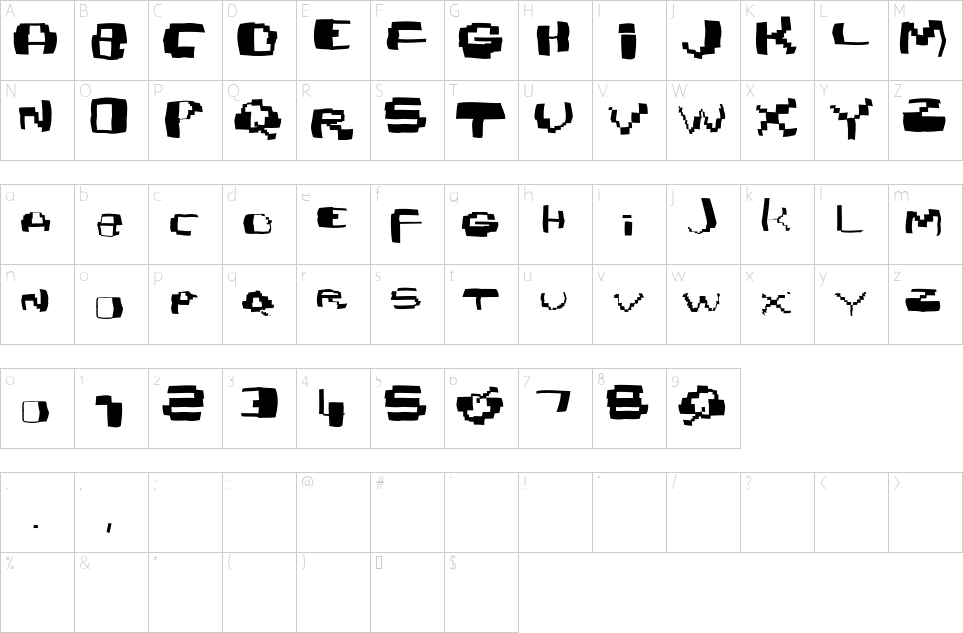
A Damaged Pix Font é uma fonte única e intrigante que traz uma personalidade única para seus projetos. Desenhada pelo designer desconhecido Manfred Klein 击破, ela combina elementos de desgaste, danos e imperfeição de uma maneira que torna qualquer texto a qual ela é aplicado um verdadeiro show de palco. Se você está procurando por algo além do convencional, essa fonte pode ser perfeita para dar aquele toque especial em seus designs digitais. É o tipo de coisa que irá chamar a atenção de quem estiver olhando, seja em uma identidade visual, em um design gráfico ou até mesmo em um logotipo. Se você busca por fontes gratuitas com estilo único e não formal, Damaged Pix Font é definitivamente algo a ser considerado. É perfeito para aqueles que querem adicionar um toque de originalidade e personalidade em seus trabalhos digitais. Não hesite em dar uma olhada neste artigo visualmente interessante e poderoso!